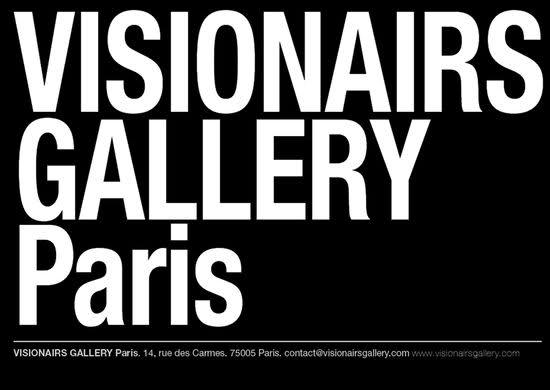
Helvetica? Aber welche?
ich bin auf der Suche nach dem Font der "Visionairs Gallery" in Paris.
Ich erkenne darin natürlich eine Helvetica. Aber genau diesen Condensed-Schnitt finde ich nirgends.
Auch WhatTheFont bringt kein zufriedenstellendes Ergebnis …
Wer kann mir denn helfen?
oh, das ist ein sehr exklusiver schnitt. weiß nicht, ob du da rankommst.
es handelt sich um die helvetica condensed bold quetsched :-D die breite beträgt ungefähr 80% der normalen condensed-variante. sehr visionär, finde ich.